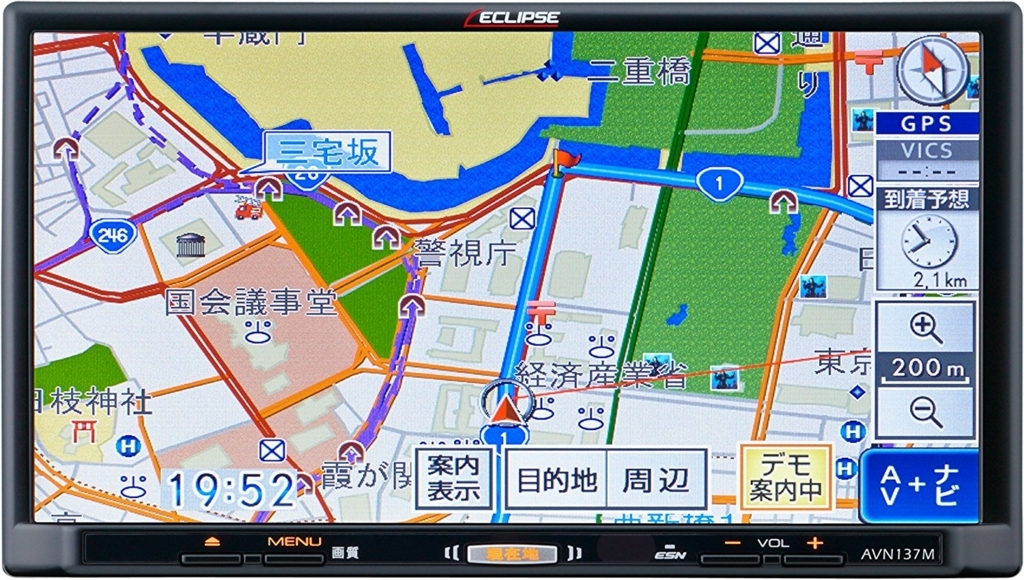
富士通テン株式会社が開発・販売するドライブレコーダー内蔵ナビ「録ナビ」にダイナコムウェアの組込み用フォントとして「UDゴシック体」が採用されている。
「イクリプス録ナビ」にダイナフォント組込みフォント「UDゴシック体」が採用
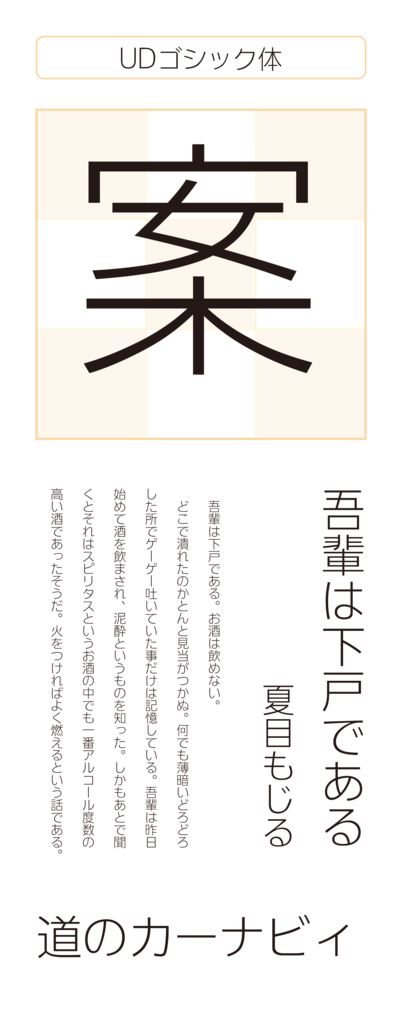
開発デザイナーがインタビューの中で、各社が展開するUDフォントを含め、様々なフォントを比較検討した際、「DFUDゴシック体」が最も美しく、そして、尖りがないフォントだと感じたと語っていた。
UDゴシック体
ユニバーサルデザイン(UD)をコンセプトにした可読性・視認性・判読性に優れたゴシック体。新聞、取扱い説明書、約款、看板などの印刷物や電子機器の表示やカーナビ、地図、スマートフォン・タブレットでも読みやすい文字として開発されている。